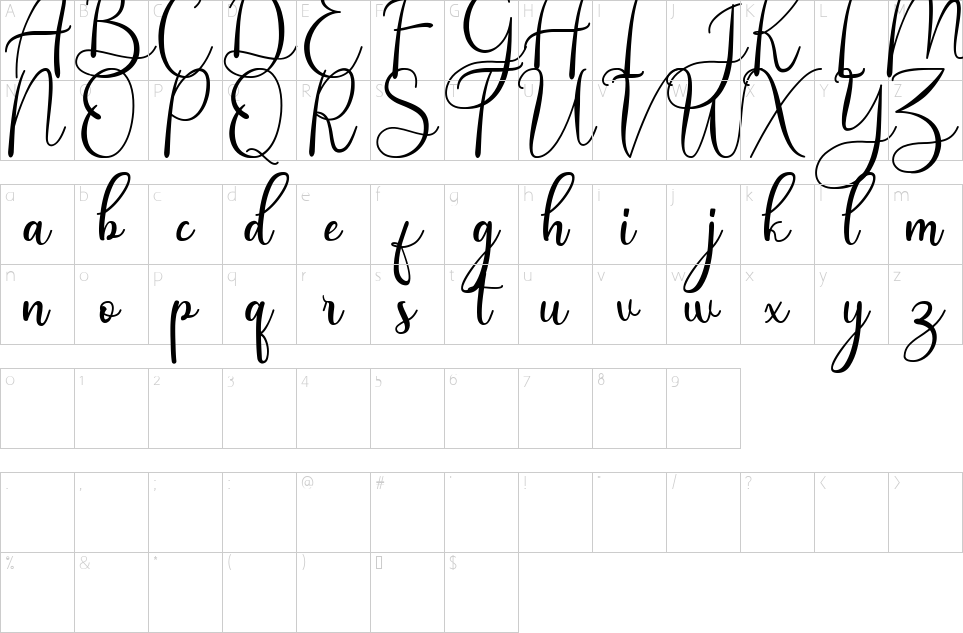
Descubra e adquira a elegante e sofisticada Andina font, perfeitamente adaptada para Windows e Mac. Esta fonte foi criada pelo Studio Sabrtype e já foi baixada 38.554 vezes. Embora não tenha sido especificado, o seu design minimalista e moderno se adapta perfeitamente a qualquer projeto, seja para o design gráfico, a criação de interfaces ou até mesmo para a escrita de letras artísticas. Com um design fluido e arredondado, Andina oferece uma excelente experiência de leitura, especialmente para textos legíveis e bem estruturados. Para qualquer profissional do design, esta fonte é uma ótima escolha, oferecendo tanto a versatilidade quanto a qualidade que você precisa para seus projetos. Descubra o encanto da Andina e faça a sua fonte favorita hoje.